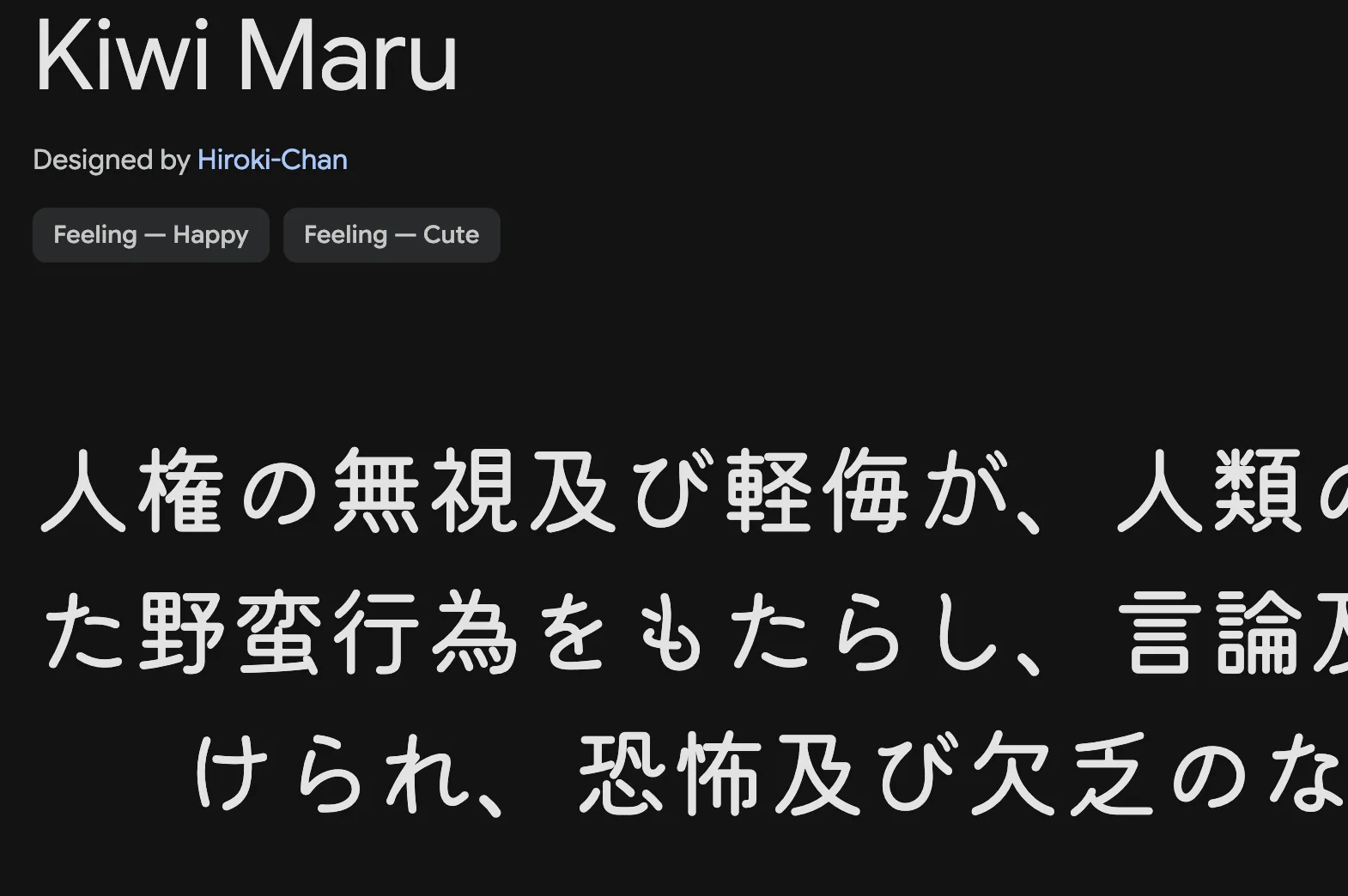
Cormorant Garamondは、Garamondの影響を受けた、優雅でクラシカルなセリフフォントです。洗練された美しさを持ち、文学的なコンテンツやアート関連のウェブサイトに最適です。上品で落ち着いた雰囲気を演出したい場合に適しています。
Rasmus Anderssonによって設計された高い視認性を持つサンセリフフォント。高いx-heightと多彩なOpenType機能を備えており、デジタル画面での使用に最適化されています。
TBUD学参常改極太丸ゴ StdNは非常に太い丸ゴシック体フォントです。大きな見出しやタイトルに最適で、子供向け教材でも視認性の高いデザインを実現します。
明朝体風で文字の先端に丸い「うろこ」がかわいらしいモダンな印象のフォント。丸いドットの装飾によってポップでかわいらしい。
文字の太さが均一で、細いセリフ体の特徴を持っているかなフォント。文字の先端にセリフ体の飾りがアクセント。
ノスタルジアと古き良き時代の魅力を喚起するシックでモダンでタイムレスなセリフフォント。そのエレガントで洗練された文字形は、洗練さと伝統的なタッチを必要とするデザインの作成に最適です。
本文に使用することを想定したスタンダードで可読性の高いゴシック体フォント。文字サイズが小さくてもつぶれにくい。
Latoは、Open SansやHelveticaに似た、クセがなく可読性の高いサンセリフフォントです。数字も美しく、使いやすいのが特徴です。柔らかい雰囲気も持ち合わせており、幅広いデザインに適用できます。
Poiret Oneは、独特な形状が特徴的なサンセリフフォントです。文字幅に大きな差があり、細いウェイトがおしゃれな印象を与えます。デザイン性の高いウェブサイトや、個性を表現したい場合に最適です。